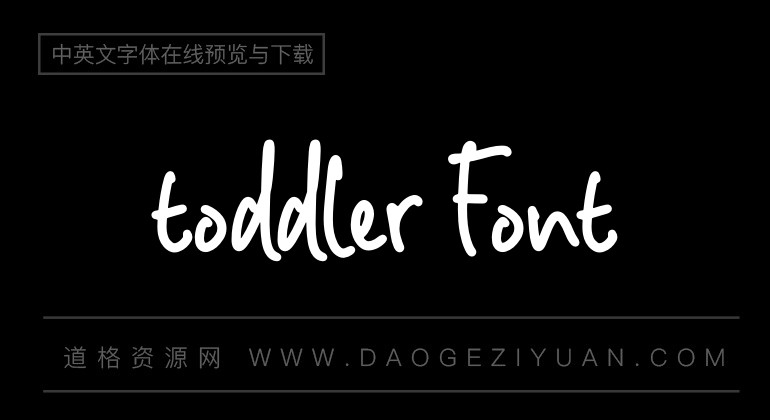
toddler Font
Toddler Font 是一种非常可爱的字体,其特点是仿照幼儿手写字体设计而成。这种字体通常由浓重的线条和简单的形状组成,适合用于婴儿、幼儿相关的设计项目中。 这种字体通常用于制作儿童书籍、玩具包装、幼儿教育卡片等设计项目。Toddler Font 字体的设计风格与孩子们自然、可爱的特点非常相似,因此可以很好地吸引孩子们的注意力,增强他们对设计项目的亲和力。 总之,如果你正在设计与幼儿相关的项目,Toddler Font 字体是一个非常有趣、有用的选择。
toddler Font是一款非常不错的手写艺术字体,具有很好的视觉感,适合于文化类的宣传设计、商业类品牌的广告和产品包装设计以及个性化文字排版等较多场景。